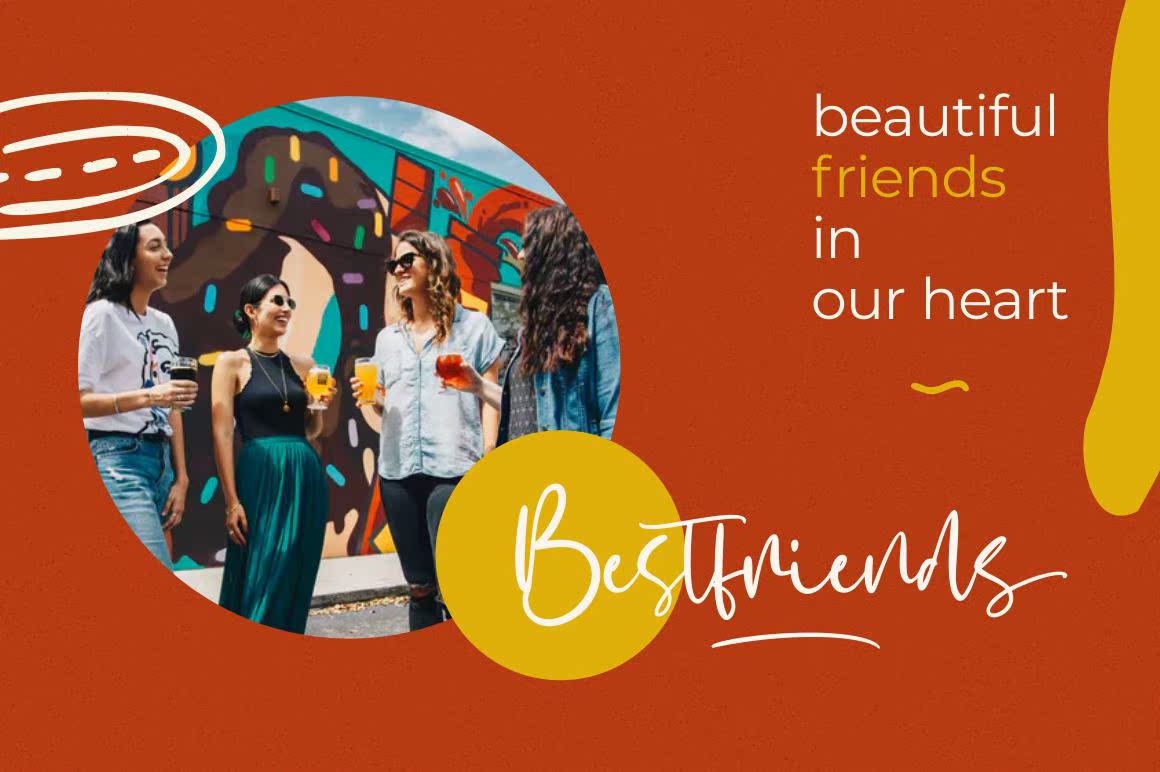
Signtype–ModernScriptFontIsa Natural&Modernhand and Written字体。我是标志、邀请函、文具、婚礼设计、社交媒体、广告、产品包装、产品设计、标签、照片、水印、特殊物品或任何东西的完美选择。此字体包括:Signtype OTF TTF WOFF、连字、,还有多种语言支持。Signtype–ModernScriptFont是一种自然的、现代的书写字体。我非常适合于徽标、邀请函、文具、婚礼设计、社交媒体、广告、产品包装、产品设计、标签、摄影、水印、特殊字体等。这种字体包括:Signtype OTF TTF WOFF、连字和多种语言支持。